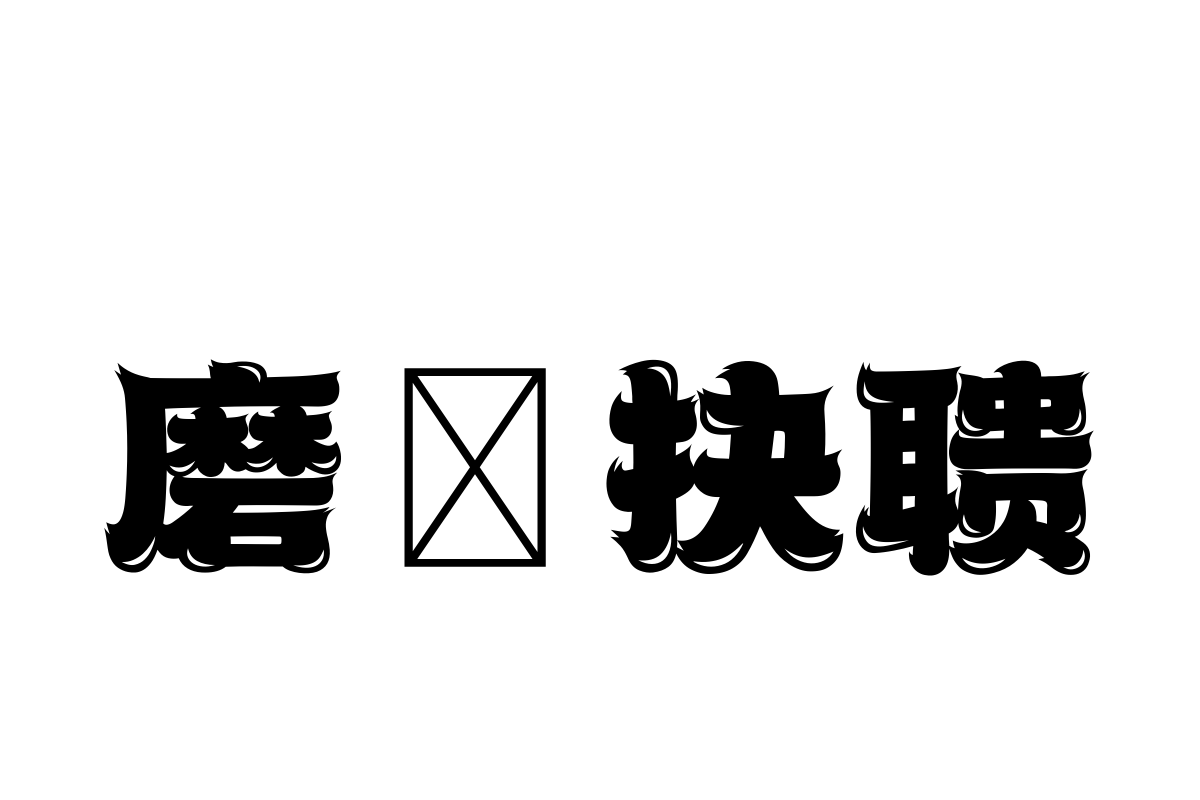
汉仪暴漫体是一款专为漫画、插画设计的中文字体。这款字体具有独特的风格和特点,使其在视觉上呈现出一种独特而有趣的效果。
首先,汉仪暴漫体的字形设计非常独特,线条流畅且富有弹性,给人一种动感十足的感觉。这种设计使得文字看起来更加生动有趣,能够吸引读者的注意力。
其次,汉仪暴漫体的笔画粗细不一,既有粗犷的线条又有细密的笔画,形成了丰富的层次感。这种设计使得文字在视觉上更加立体,能够更好地表达出作者的情感和意境。
此外,汉仪暴漫体的字体风格也非常适合用于漫画、插画等艺术创作,能够为作品增添一份独特的韵味。无论是人物形象还是场景描绘,都可以借助汉仪暴漫体的字体来展现其独特的魅力。
总的来说,汉仪暴漫体是一款非常适合用于漫画、插画等艺术创作的中文字体。它的独到设计和丰富表现力,使得作品更具吸引力和表现力,能够更好地传达作者的情感和思想。